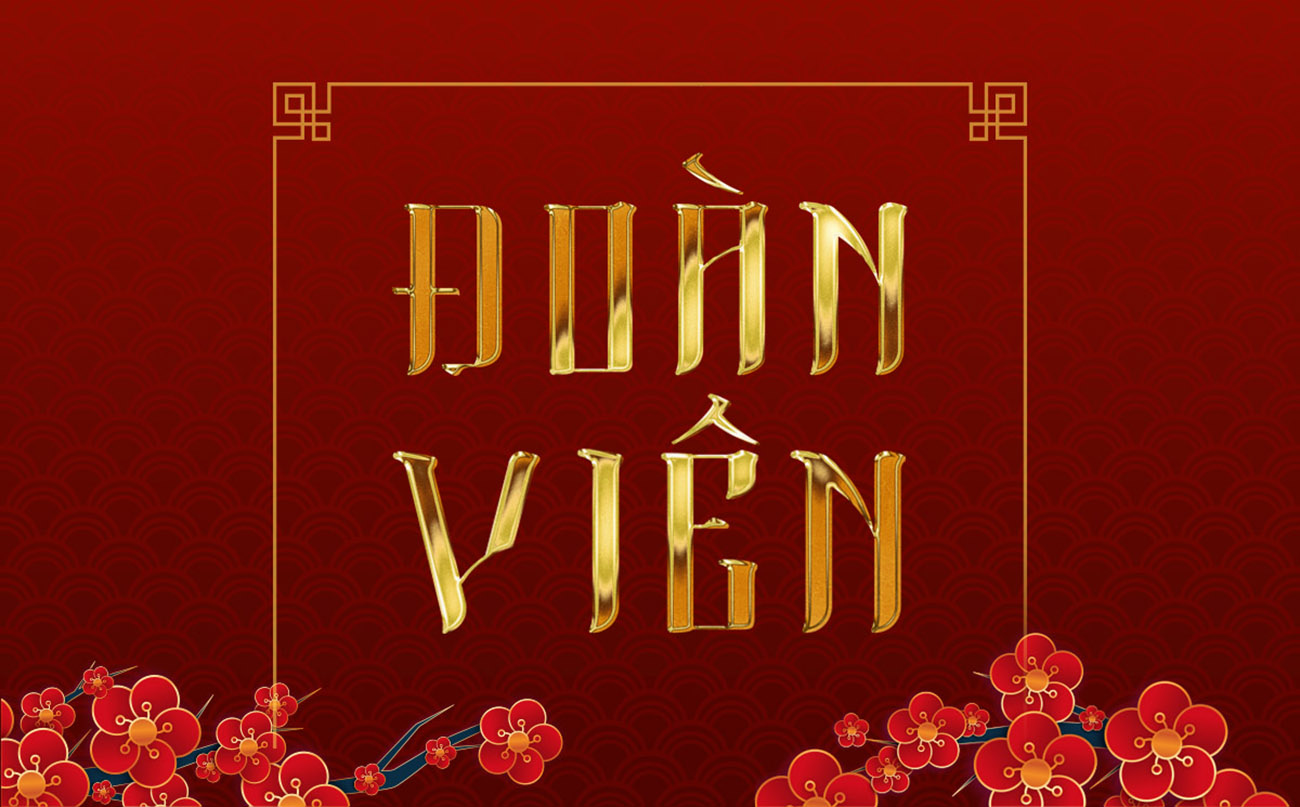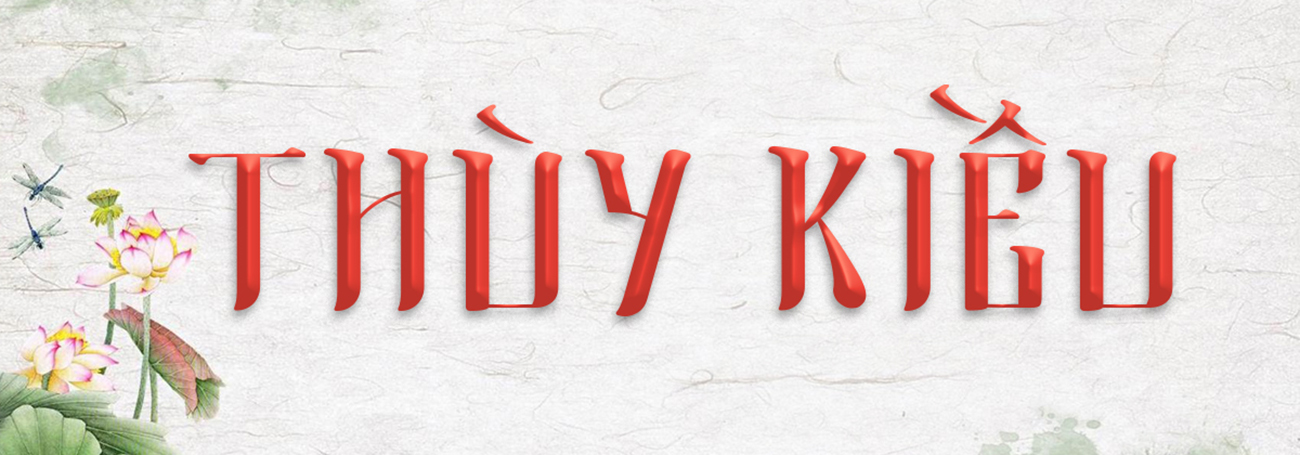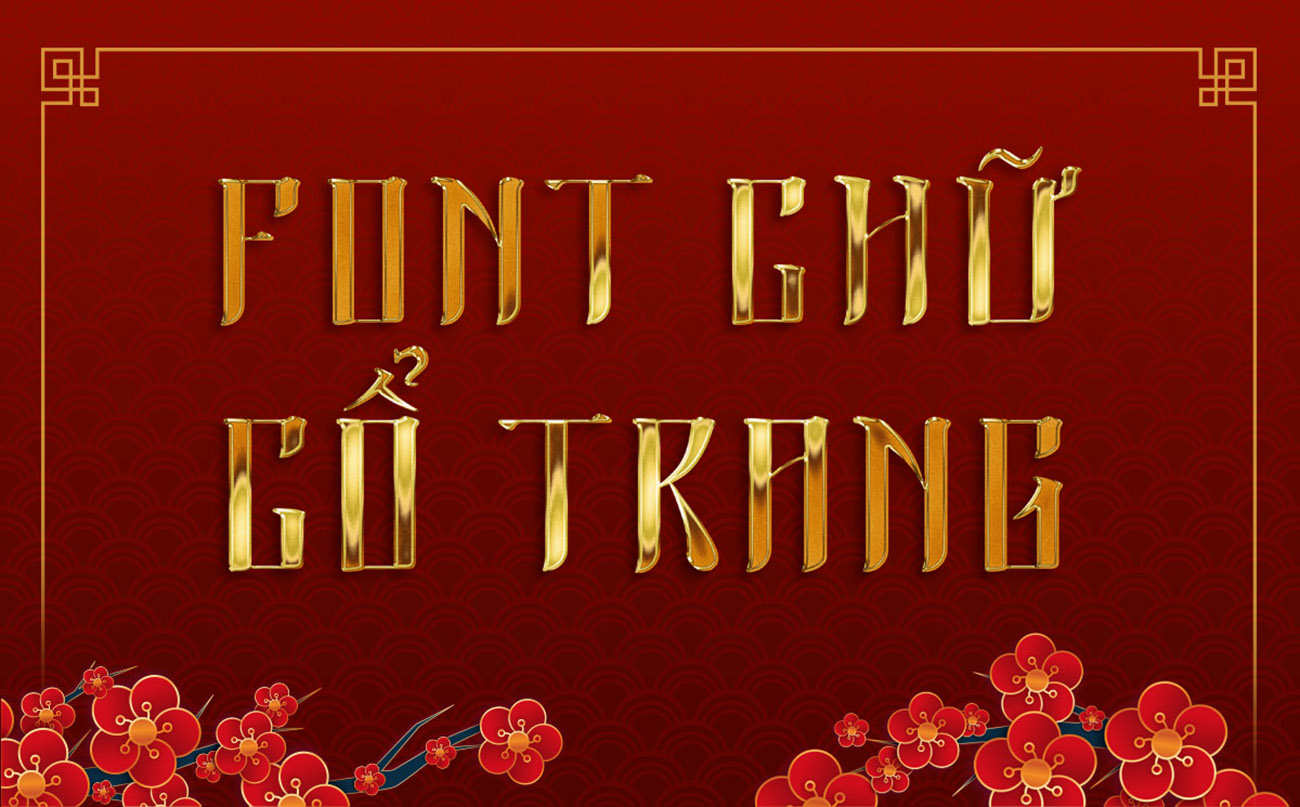
Phông chữ phong cách cổ trang Việt hóa - NVN Morning Calm
Tác giả Kim JinHyuk
Việt hóa Team NVN
1. Giới thiệu tổng quan về font NVN Morning Calm
Khi nhắc đến những thiết kế mang đậm hơi thở hoài cổ, phong cách Á Đông hoặc không khí cổ trang thanh tịnh, một trong những yếu tố quyết định sự thành công chính là lựa chọn font chữ. Trong số đó, font cổ trang NVN Morning Calm là một cái tên nổi bật, mang lại cảm giác thư thái, chuẩn mực và đầy tinh tế cho mọi ấn phẩm bạn tạo ra.
NVN Morning Calm là phiên bản Việt hóa hoàn chỉnh từ font chữ Morning Calm – một thiết kế của Kim JinHyuk, nhà thiết kế người Hàn Quốc. Bộ font này gây ấn tượng bởi sự kết hợp hài hòa giữa nét thanh lịch kiểu serif phương Tây và hơi thở trầm mặc, tĩnh tại của văn hóa phương Đông. Khi được Việt hóa bởi team NVN, font đã được bổ sung đầy đủ dấu tiếng Việt, đảm bảo tính ứng dụng cao trong các thiết kế in ấn và số hóa hiện đại.
2. Phong cách thiết kế & cảm hứng cổ trang
Ngay từ cái tên “Morning Calm” – dịch nghĩa là "sự tĩnh lặng ban mai", font đã gợi ra hình ảnh của những khung cảnh cổ trang: ánh nắng nhẹ xuyên qua màn sương mỏng, bức thư tay viết bằng nét chữ mềm mại, hay khung cảnh một ngôi chùa cổ giữa núi non trùng điệp. Đây là cảm hứng xuyên suốt của bộ font – một sự giao hòa giữa vẻ đẹp tĩnh tại và sự chuẩn mực trong từng đường nét.
Dáng chữ serif nhẹ, thanh thoát, cùng độ tương phản rõ giữa nét đậm và nét thanh khiến mỗi ký tự trong NVN Morning Calm mang đến cảm giác như được viết bằng bút lông hay mực tàu – gợi nhớ đến thư pháp, nhưng vẫn giữ được sự cân đối và dễ đọc. Chính sự hòa quyện này giúp font trở thành font cổ trang lý tưởng cho các dự án mang đậm màu sắc văn hóa hoặc lịch sử.
3. Đặc điểm nổi bật của font cổ trang NVN Morning Calm
• Thiết kế thanh lịch, dễ đọc: Dù mang cảm hứng cổ trang, nhưng NVN Morning Calm vẫn đảm bảo tính dễ nhìn, phù hợp cho cả văn bản dài hoặc tiêu đề.
• Nét chữ mềm mại, có chân (serif): Các serif được xử lý tinh tế, mang lại cảm giác sang trọng mà vẫn gần gũi.
• Tương thích tiếng Việt đầy đủ: Phiên bản Việt hóa được team NVN thực hiện kỹ lưỡng, hỗ trợ đủ dấu thanh, nguyên âm đôi – ba, và ký tự đặc biệt.
4. Ứng dụng trong thiết kế cổ trang & nghệ thuật
Font cổ trang NVN Morning Calm không chỉ phù hợp với các dự án mang yếu tố hoài niệm, mà còn cực kỳ lý tưởng cho nhiều lĩnh vực khác như:
• Thiết kế bìa sách lịch sử, tiểu thuyết cổ trang
• Poster phim cổ trang, sân khấu kịch truyền thống
• Ấn phẩm văn hóa – nghệ thuật như thiệp chúc Tết, thiệp thư pháp
• Tranh in quote, thơ cổ, văn học dân gian
• Các dự án branding gắn với yếu tố truyền thống, như nhà hàng phong cách Á, studio áo dài, thương hiệu mỹ phẩm Đông y…
Chỉ cần chọn đúng ngữ cảnh và bố cục thiết kế, NVN Morning Calm có thể làm nổi bật nội dung truyền tải một cách đầy nghệ thuật mà không cần thêm nhiều hiệu ứng phức tạp.
Tổng kết
Trong thế giới thiết kế đòi hỏi sự cảm thụ tinh tế và tính thẩm mỹ cao, font cổ trang NVN Morning Calm chính là lựa chọn không thể bỏ qua cho những ai yêu thích sự nhẹ nhàng, cổ điển và chuẩn chỉnh trong từng ký tự. Font không chỉ mang đậm tinh thần Á Đông mà còn đáp ứng trọn vẹn các yêu cầu kỹ thuật, giúp bạn dễ dàng đưa ý tưởng thiết kế từ cổ tích đến hiện đại vào cuộc sống.
Dù bạn là designer chuyên nghiệp hay người yêu thích sáng tạo thủ công, hãy thử trải nghiệm NVN Morning Calm – để từng dòng chữ trở nên sống động và đầy cảm xúc.